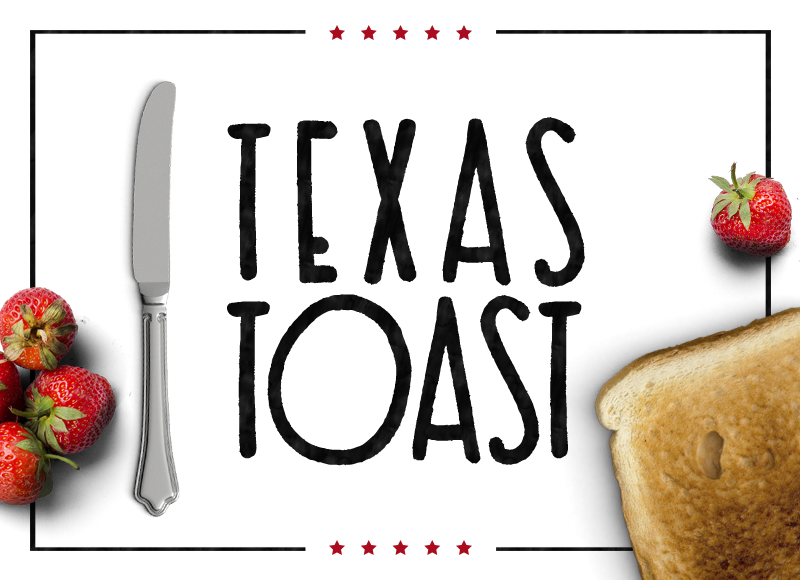
Texas Toast Font
A fonte Texas Toast é uma opção retro perfeita para aqueles que valorizam os tempos dos computadores de velha geração. Criada pelo designer Hamilton, esta fonte tem um charme único e suave, ideal para aplicativos pessoais como cartões de natal ou aniversários, mensagens de WhatsApp personalizadas ou até mesmo para fins educacionais em projetos escolares. Para uso comercial, é importante ter a autorização do criador. Para obter mais informações ou fazer seu pedido, basta enviar um e-mail para . Com sua elegância minimalista e capacidade de adicionar um toque retro a qualquer projeto, Texas Toast é uma excelente opção para tornar seus materiais ainda mais únicos e divertidos.